本わさびを頭皮に塗り込めばハゲが治る説
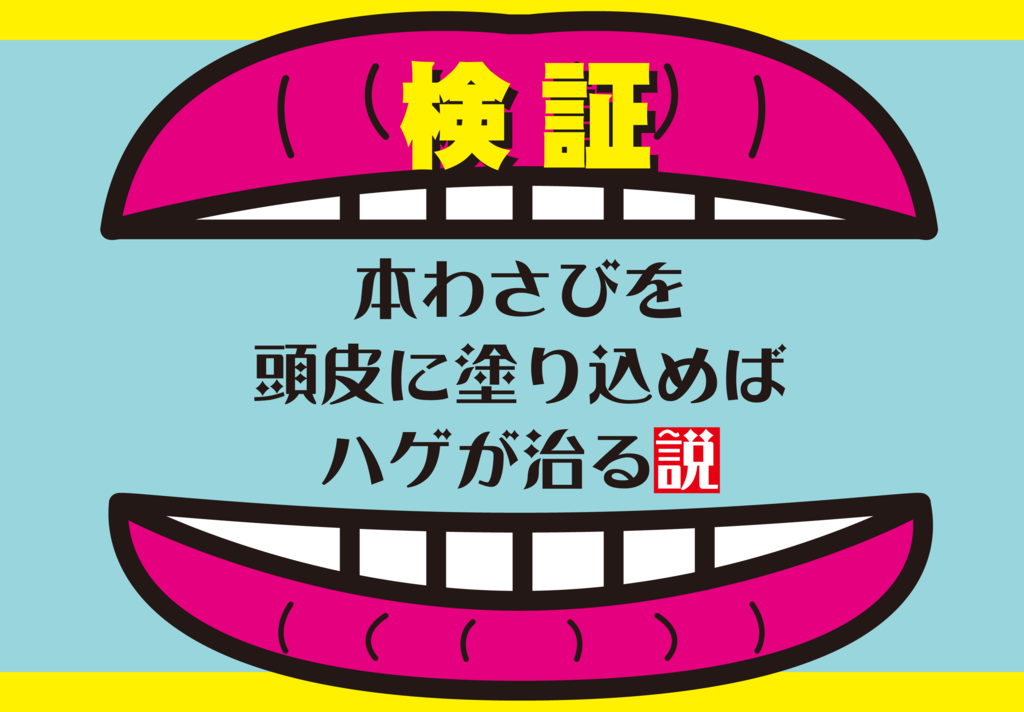
本わさびの葉からはアンチエイジングに効果があるポリフェノールの一種「イソサポナリン」成分を抽出できる。ヒトの頭皮の毛根にある発毛に関する物質伝達をつかさどる「毛乳頭細胞」に「イソサポナリン」を加えて培養することで細胞が活性化する効果が観察された。
この活性化は市販の育毛剤の有効成分に使用される「ミノキシジル」を加えた場合の3倍に達したそうだ。
育毛を促すメカニズムについては、イソサポナリンの働きにより毛乳頭細胞が外部からの刺激を受け取る「受容体(レセプター)」の感受性が高まり、細胞を活性化させることが判明。毛髪をつくるのに必要な栄養などを毛乳頭細胞に送り届けるための毛細血管をつくるタンパク質が増えることも分かった。
この他に本わさびの根茎に含まれる辛味成分の一種である「6-MSITC」をヒトの毛乳頭細胞に投与した実験においても同様の効果やメカニズムが観察された。この育毛を促す2つの成分は本わさび特有のものでチューブ入りわさびの多くに使われる西洋わさびには含まれていないことも分かった。
わさびで育毛の活用例の文字はダイナフォント 爽流体を使用
細くて多様性のある横画、太い左払いと右払い、そして規則のない円形の点で構成することによって、まるで軽やかに躍っている波平の一本毛のよう。
爽流体はダイナコムウェアが開発・販売するダイナフォント(DynaFont)シリーズのフォント(書体)であり、有料フォントとなっている。